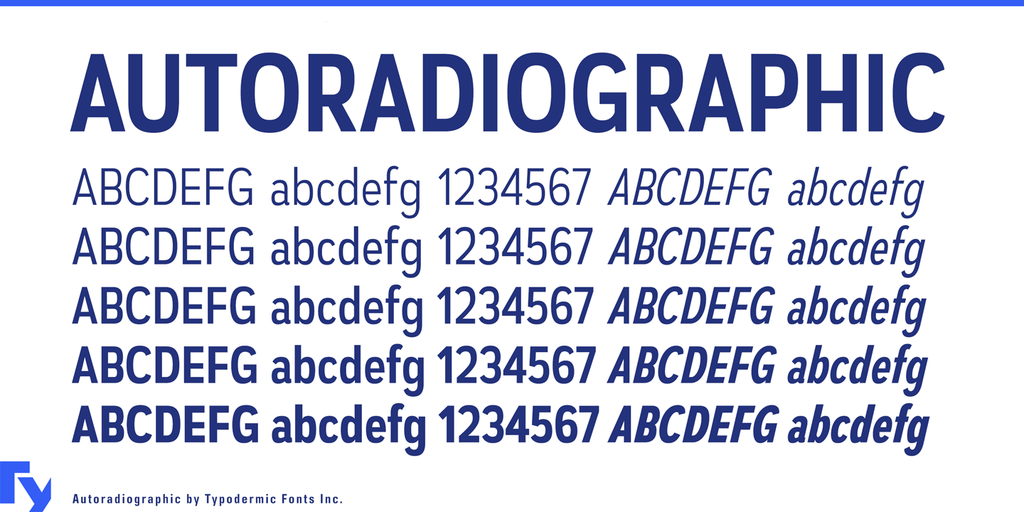
Autoradiographic Font Family
A Autoradiographic é uma família de fontes gergais inspirada em sinais de advertência pintados a mão no final do século XX. Inspirado no estilo técnico e limpo dos anos 50, este conjunto de cinco pesos se assemelha aos famosos sinais de advertência encontrados nas ruas, onde o propósito era comunicar informações claras e técnicas, mesmo que um leve toque pessoal escapasse. Este design é perfeito para uso em letras informativas no desktop, incluindo símbolos matemáticos e círculos monetários, sem esquecer os caracteres gregos e cirillico. Nossa família de fontes Autoradiographic também contém itálico com linhas estreitas e espaçamento levemente mais amplo, destinado a dar um forte destaque à importância da mensagem. Para o uso em computadores pessoais, os estilos Regular e Italic estão gratuitos de forma a facilitar ainda mais sua integração na vida diária. Através dessa fonte elegante e funcional, você pode garantir que as suas mensagens informativas não fiquem sem destaque.